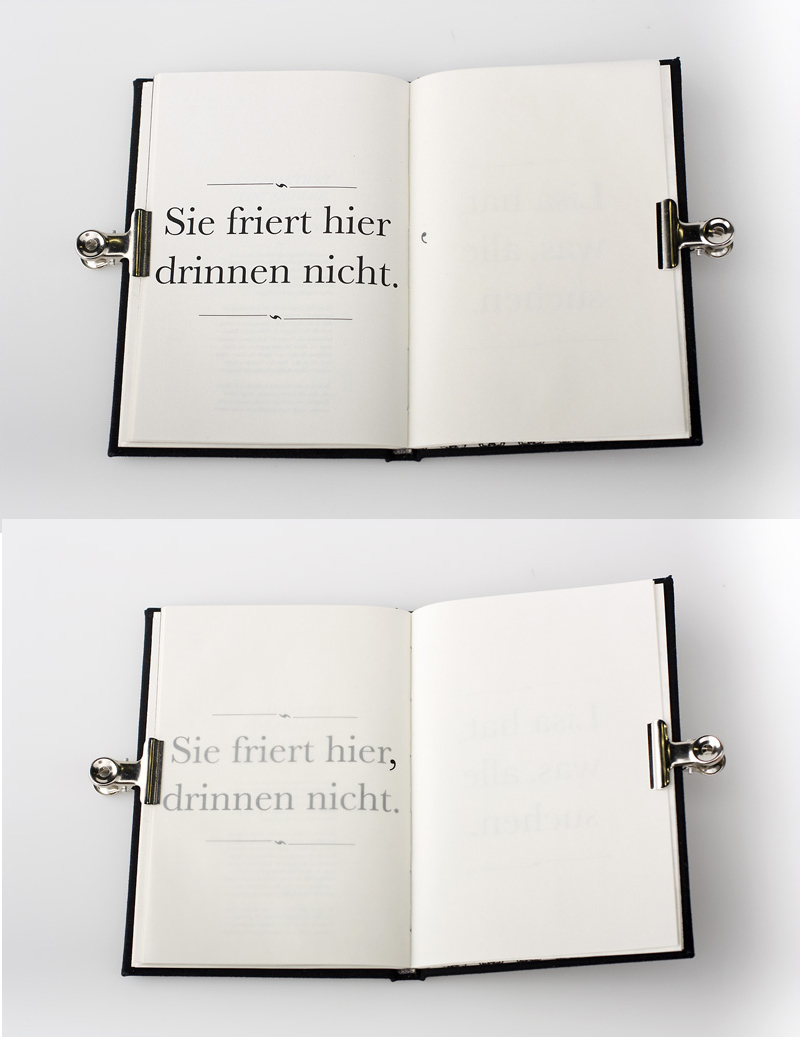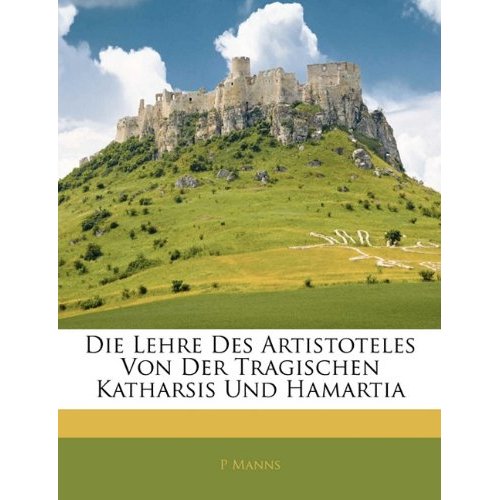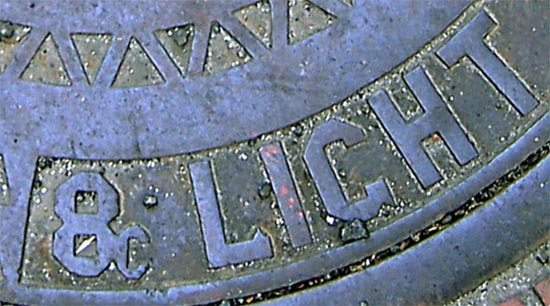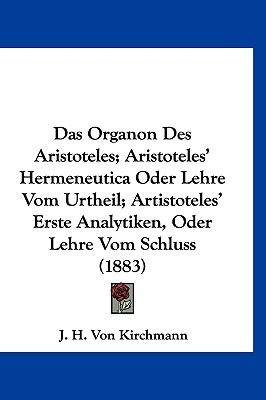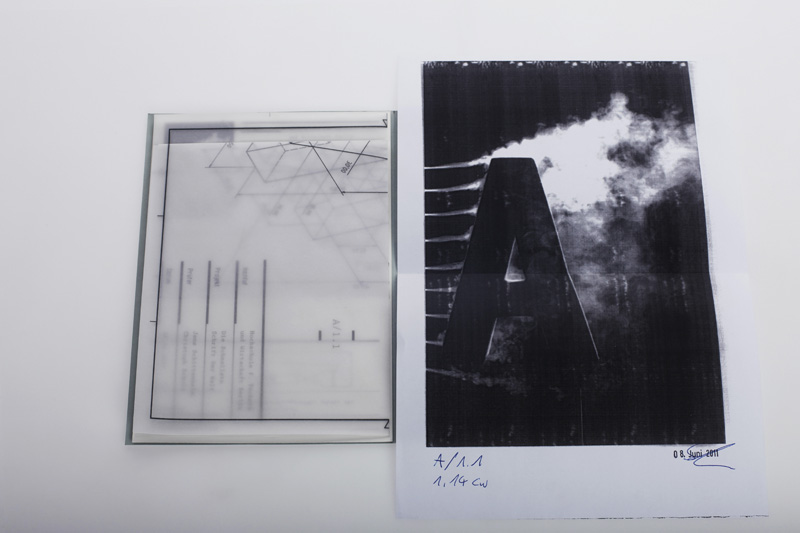
Aus reinem Unwissen gefragt: Kann das sein, dass das wirklich eine alte Schreibweise für den guten Mann ist?
tut mir leid kathrin, ad hoc weiss ich auch keine lösung außer einem scheinbar beliebten schreibfehler. in den lexika und der literatur, die ich zu hause bzw. zu der ich grad online zugang habe, findet sich keine erklärung zu dieser schreibung.
Vielleicht kann Pachulkes Tochter ja mal ihren Griechischlehrer fragen, ob der die Lösung weiß.
Lach! Es eilt ja nicht. Die Ungewissheit, ob ich eine Bildungslücke habe oder nicht, ertrage ich schon noch ein Weilchen. ;-)
ein bischen weitergesucht. der name kommt in der digitalisierten antike nicht vor (basis: tlg-e und aktuelle phi). hast du den ganzen spruch? dann könnten wir über das zitat vielleicht den autoren suchen. google erweckt zudem den eindruck (via fight und ngram), dass es sich wirklich um einen verschreiber handelt.
… google erweckt zudem den eindruck (via fight und ngram), dass es sich wirklich um einen verschreiber handelt.
Das denke ich auch … nur – wie kommt es dann zu den Buchtiteln?
Ich habe noch ein paar Bruchstücke, aber nicht den ganzen Spruch, fürchte ich … Die Perspektive dort war ziemlicher Mist zum Fotografieren.
Wäre von Aristoteles ohne t.
wie kommt es dann zu den Buchtiteln?
mieses lektorat würd ich schätzen. begegnet mir häufiger in nichtspezialisierten verlagen (manchmal auch in diesen, wie ein blick in google scholar zeigt), dass mit altsprachlichen/altgeschichtlichen dingen geschludert wird. das passiert, wenn man das lektorat durch billige kräfte ersetzt, die zudem häufig nicht nur fachfremd, sondern auch noch - vorurteilsmäßig - fern einer universitären respektive humanistischen bildung sind.
"Die Lehre des Artistoteles …" This is a reproduction of a book published before 1923. This book may have occasional imperfections such as missing or blurred pages, poor picture.
Wird als print on demand hergestellt. Eventuell wurde der falsche Titel von damals übernommen?
glaube ich nicht. eher ist ein ocr-fehler. hier hat mal ein setzer daneben gegriffen: http://books.google.de/books?id=20sMAAAAYAAJ&dq=artistoteles&hl=de&pg=PA166#v=onepage&q=artistoteles&f=false (ältester fund auf den ersten seiten, sonst nur treffer im 20./21. jhd.)
da aber auch in den texten mit artistoteles aristoteles häufiger genannt wird, muss das irgendeine komische fehlleistung des hirns sein... *g*
Drüben bei Design made in Germany ging es heute neben Eriks Video weiterhin sehr schriftfreundlich zu.
So wurde heute ein charmantes Loblied für das Komma angestimmt:
»Das kleine Schwarze« (Ein Buchprojekt von Johanna Fuchs)
Und auch der skurrile Versuch, die »Aerodynamik« von Schrift zu untersuchen, könnte dem einen oder anderen Typofreund unter uns ein Schmunzeln abringen:
»Die Schnellste Schrift …« (Bachelorarbeit von ChristophSchulz und Jens Schittenhelm)
Man beachte das &, das eher wie 8c aussieht …
Wahrscheinlich, weil man auf biegen und brechen die eckig-geometrische Konstruktion durchhalten wollte? Vielleicht war man auch einfach zu faul … :-?
Solche Gußformen werden halt selten von Typographen gestaltet sondern eher von Modelltischlern, deren typographisches Verständnis recht unterschiedlich ausfällt.
Der wird halt nix anderes im Setzkasten gehabt haben – da sind schnell eine 8 und ein c zu einem & zusammengebastelt. Seien wir froh, dass er nicht das ẞ erfunden hat … ;-)